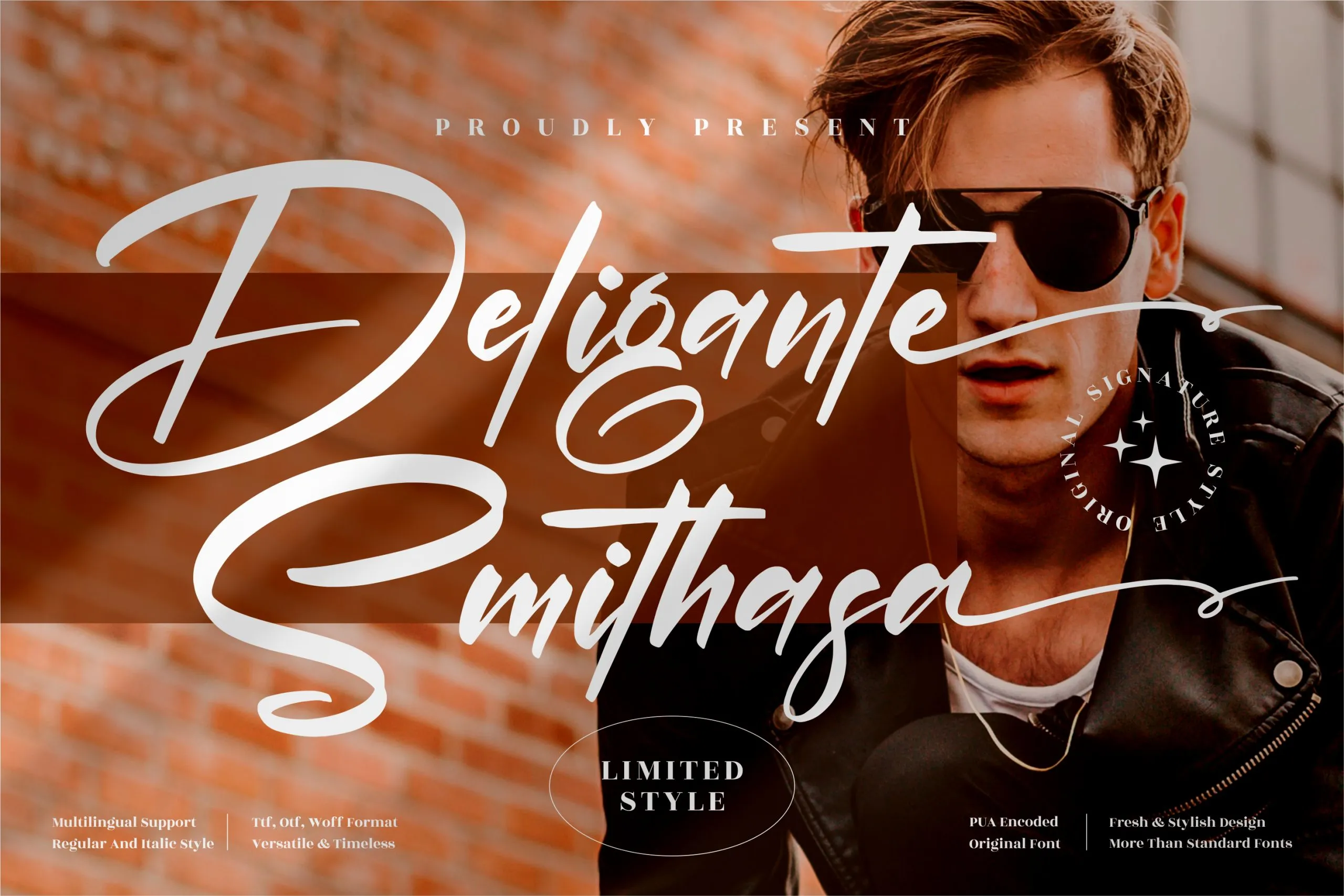
Deligante Smithasa é uma fonte de estilo autêntico e elegante criada pela Perspectype Studio. Ela combina a modernidade de linhas retas com um toque sofisticado, tornando-a perfeita para qualquer projeto que deseja um ar de sofisticação premium. A fonte Deligante Smithasa é uma opção ideal para designers de logotipos e projetos de marca, bem como para designers de embalagens de produto ou até mesmo em designs de etiquetas. O seu estilo autoral torna-a perfeita para adicionar um toque único a qualquer projeto, desde as cenas mais simples de nome cards até aos maiores eventos especiais. Com Deligante Smithasa, você pode garantir que todos os seus projetos tenham uma qualidade premium e sofisticação, sem dúvida capaz de destacar-se entre outros materiais. Seja para criações minimalistas ou com um toque mais elaborado, a font Deligante Smithasa está aqui para tornar seu trabalho ainda melhor.